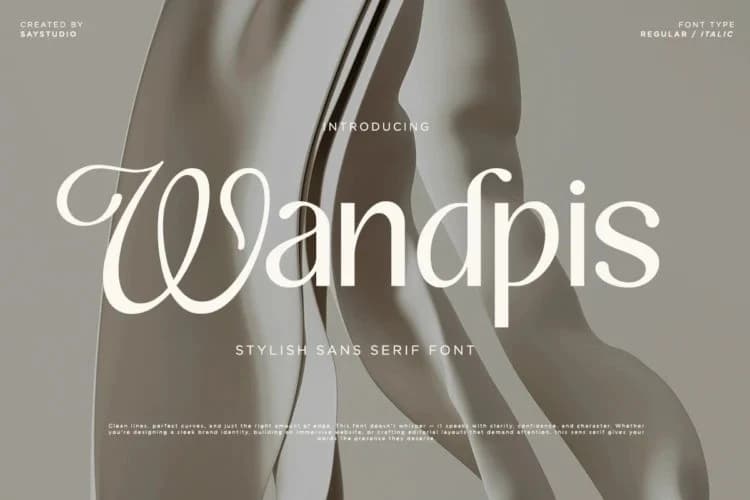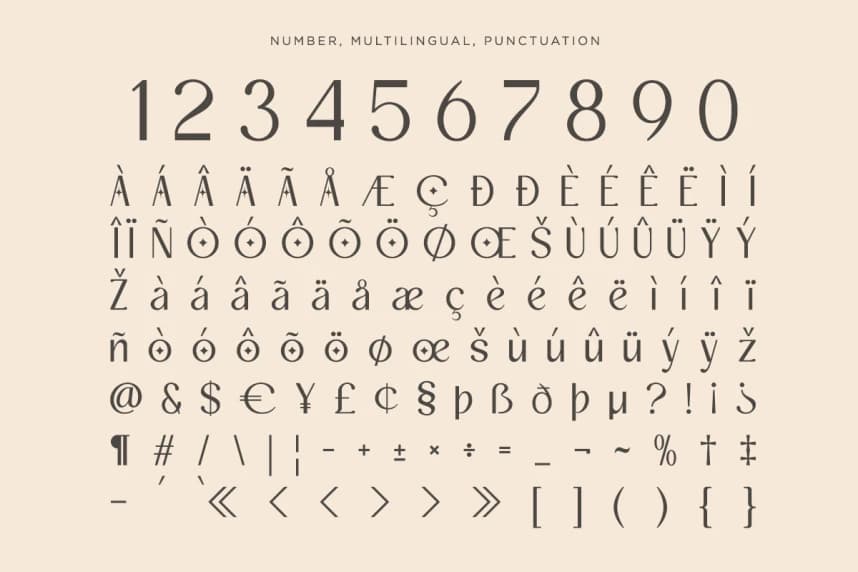
Wandpis Font
Wandpis Font, zarif marka kimliği ihtiyaçları için özel olarak tasarlanmış şık bir sans serif yazı tipidir; benzersiz biçimiyle markanıza değer katmaya hazırdır. Tasarımını daha lüks ve modern kılmak isteyen tasarımcılar veya ürün sahipleri için kullanışlıdır.
Wandpis Font, zarif bir markalaşma ihtiyacına özel olarak oluşturduğumuz şık bir sans-serif yazı tipidir; benzersiz şekli markanıza değer katmaya hazırdır. Tasarımcılar veya tasarımına çözümler arayan ürün sahipleri için tasarımınızı daha lüks ve modern göstermeye yardımcı olur.